Bạn đang tìm kiếm những font chữ độc đáo để làm nổi bật thiết kế của mình? Với graffiti – nghệ thuật đường phố, từng kiểu chữ có thể biến ý tưởng của bạn thành tác phẩm ấn tượng. Bộ sưu tập [Free download] 30+ Font chữ Graffiti đẹp dưới đây sẽ là lựa chọn hoàn hảo cho poster, logo hay banner hiện đại.
Đặc trưng Font chữ Graffiti là gì?
Font Graffiti xuất phát từ nghệ thuật đường phố, nơi mà những dòng chữ được thể hiện trên tường, ga tàu hay khu phố bằng sơn xịt. Điểm nổi bật của kiểu chữ này nằm ở sự phóng khoáng, tự do và đậm cá tính, phản ánh tinh thần sáng tạo không giới hạn.
Các đặc trưng thường thấy của font Graffiti:
- Dạng block và uốn lượn: nhiều chữ cái được thiết kế thành khối lớn, dày dặn hoặc kéo giãn, tạo hiệu ứng mạnh mẽ.
- Đường nét phóng khoáng: không theo khuôn mẫu cứng nhắc, thể hiện sự ngẫu hứng của nghệ sĩ.
- Hiệu ứng sơn xịt: mô phỏng màu sơn loang, bắn tung tóe, tạo cảm giác chân thực như một tác phẩm Graffiti trên tường.
- Đa dạng phong cách: từ chữ nét tròn mềm mại đến chữ góc cạnh sắc bén, phù hợp nhiều chủ đề thiết kế khác nhau.
Chính nhờ những đặc trưng này, font chữ Graffiti thường được ứng dụng trong poster, logo, banner, áo streetwear hay thumbnail YouTube, mang lại dấu ấn đậm chất đường phố và cá tính.
10+ font Graffiti hot ngày nay
Graffiti không chỉ là nghệ thuật đường phố mà còn trở thành cảm hứng trong thiết kế số, từ poster, banner, logo đến typography sáng tạo. Dưới đây là những font Graffiti được cộng đồng thiết kế yêu thích hiện nay.
Top font Graffiti cực chất khiến dân thiết kế mê mẩn
Wildstyle Graffiti – phong cách phá cách, đường nét phức tạp, thường khó đọc nhưng lại cực kỳ ấn tượng, phù hợp cho logo và poster nghệ thuật.
Tag Type – đơn giản, dễ nhận diện, thích hợp cho các thiết kế cần tính nhanh gọn như banner hoặc chữ ký đường phố.
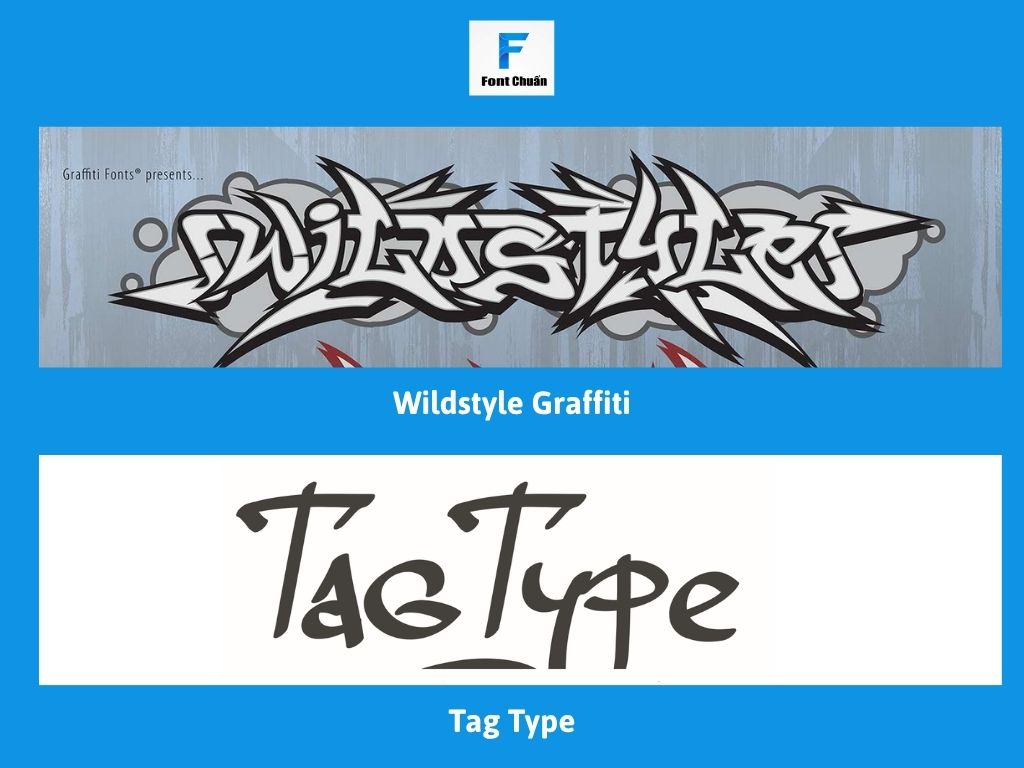
Bombing Font – đậm, rõ ràng, dễ tạo điểm nhấn trong thiết kế poster quảng cáo hoặc tiêu đề video.
Graffiti Treat – mang màu sắc cartoon street, vui nhộn và trẻ trung, hợp thiết kế dành cho giới trẻ hoặc game.
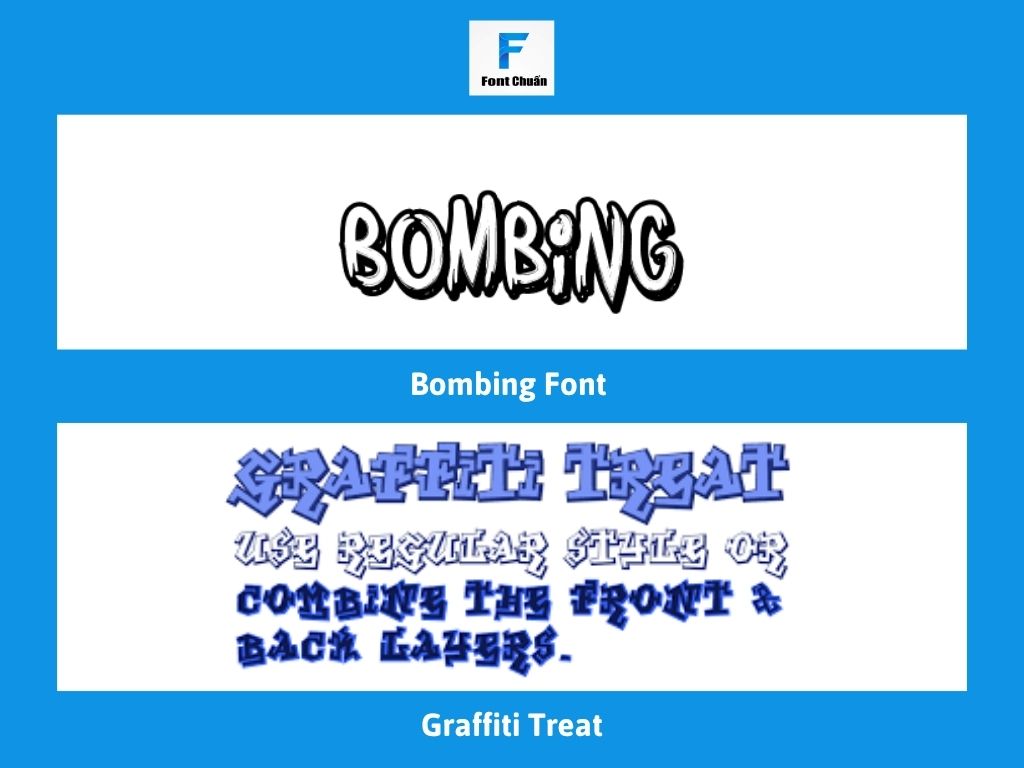
Font chữ Graffiti Việt hóa, không lo lỗi font
Nhu cầu font Graffiti Việt hóa ngày càng tăng bởi thiết kế tại Việt Nam cần font hỗ trợ Unicode để gõ tiếng Việt có dấu, tránh lỗi hiển thị. Một số font Việt hóa nổi bật:
Urban Jungle Việt hóa – font mạnh mẽ, góc cạnh, đậm chất đường phố.
BlowBrush Việt hóa – dạng cọ vẽ, mang đến cảm giác phóng khoáng, sáng tạo.
Street Soul Việt hóa – đầy đủ Unicode, vừa giữ được tinh thần Graffiti nguyên bản vừa hỗ trợ tiếng Việt mượt mà.